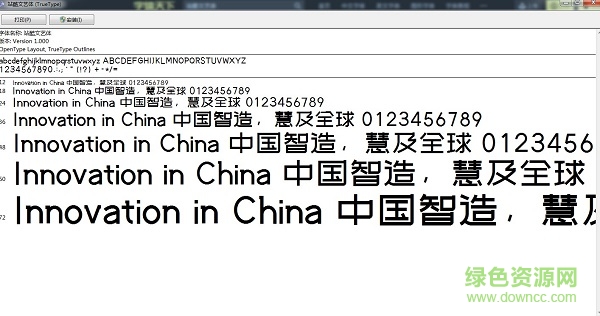
站酷文藝體otf是一款具有文藝氣息的字體,收錄了7千多個(gè)常用漢字以及常用的標(biāo)點(diǎn)符號(hào),字形勻稱美觀,閱讀效果良好,需要商用的朋友可到官網(wǎng)要求授權(quán),有需要者歡迎免費(fèi)下載!
由字體設(shè)計(jì)師劉兵克確定字形和規(guī)范,由劉兵克工作室以及劉兵克字體設(shè)計(jì)直播課學(xué)員共同創(chuàng)作完成,設(shè)計(jì)師鄭慶科完成了最終的字庫生成工作。字形新穎獨(dú)特,簡(jiǎn)潔有力,清新淡雅,文藝范十足。